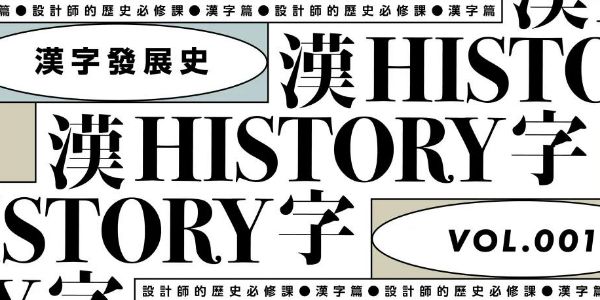
设计师的历史课——汉字篇
良好的学习方法,需要兼顾理论与实践的并行,对于设计学习来说,同样也是如此。而今天要与大家分享的,与这些都无关,却仍然十分重要,它就是历史知识。那么我也不卖关子啦,今天要讲的正是汉字的发展历史。
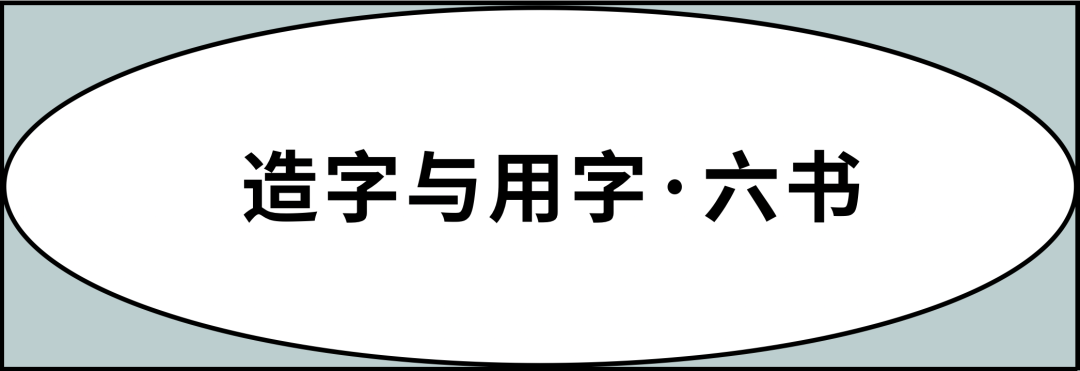
在正式介绍汉字的发展历史之前,我们有必要先来了解一下「六书」。六书,是汉字的六种造字或用字的方法,分为:象形、指事、形声、会意、转注和假借。
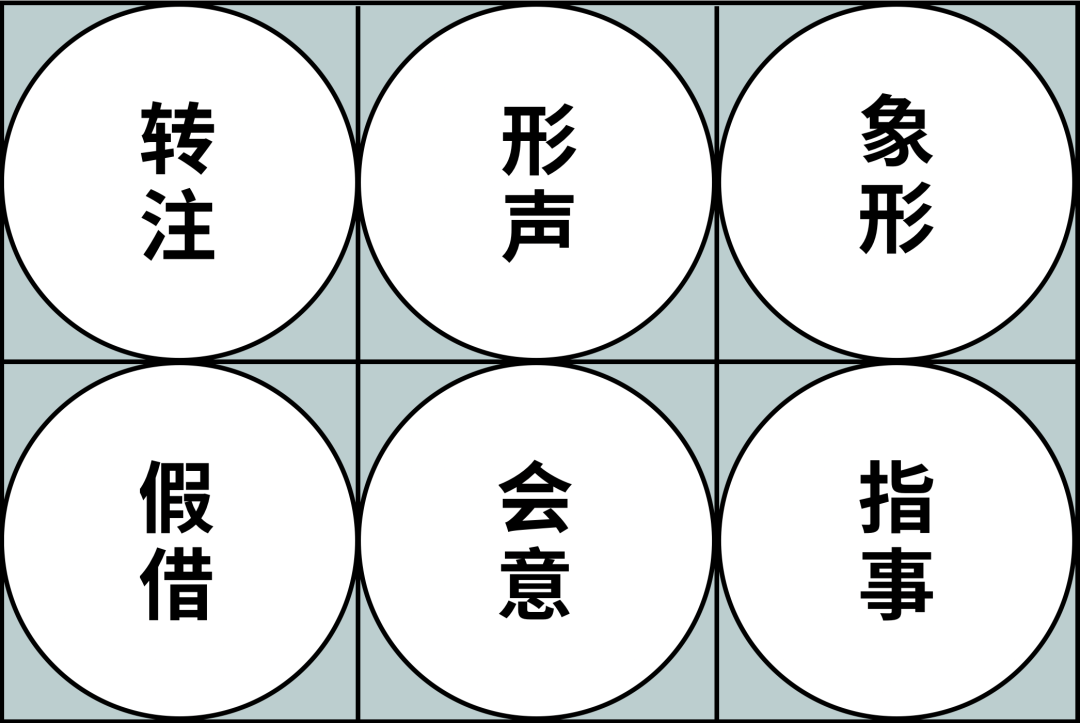
值得注意的是,六书是后人根据汉字的形成所做的归纳整理,它并不是造字公式,却也是我们应尽量追随的造字原则。要知道,现在国内所用的简体字或多或少存在的一些问题,就与脱离了这些标准离不开关系。
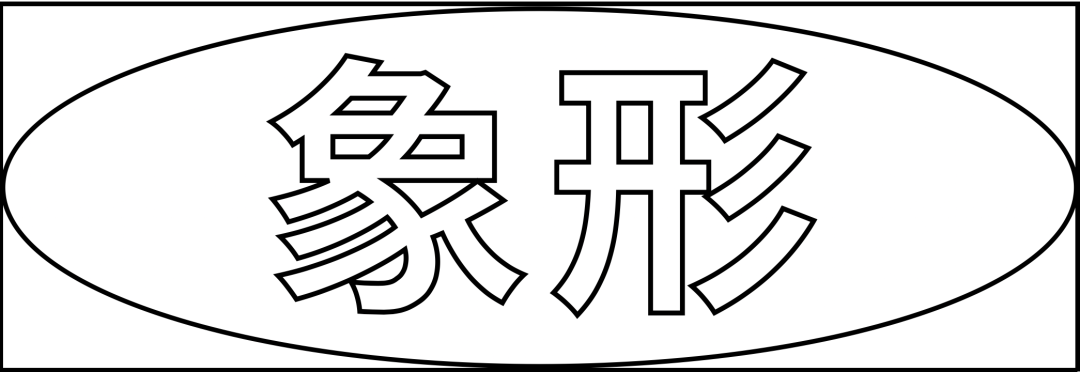
咱们先来说一下象形。象形是指根据具体事物来画出简单概括的图形,它的符号性是很明显的,强调对象的外形特征,因而是一种最简单的造字法。那么相对的,它也是很难去表达抽象的意义或没有具体形象的概念。
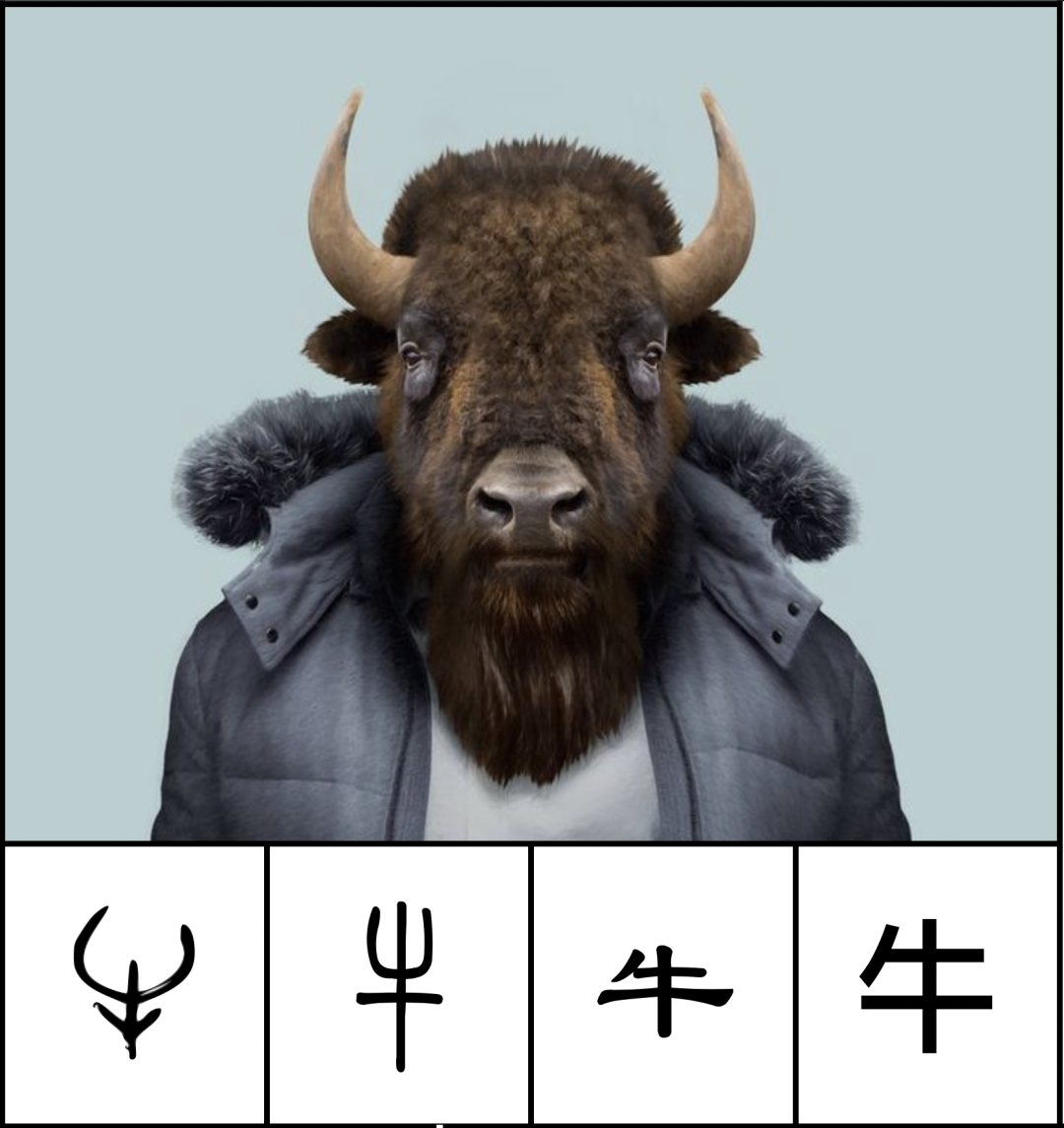
十二生肖中,就有大量的象形字,比如说「牛」字,我们看最左边的甲骨文写法,就很明显能看出是一个牛头的正面概括。
再比如这个「马」字,也是很具有代表性,同样看甲骨文版本,能够清晰地看到马鬣和马腿,并且呈一个两腿跃起的动态,描绘得还是十分生动的。而单看现在所用的简体「马」字,并不会这么明显,但是我们看这个从左往右的演化过程就豁然开朗了,这是一个标准的汉字抽象化的进程。
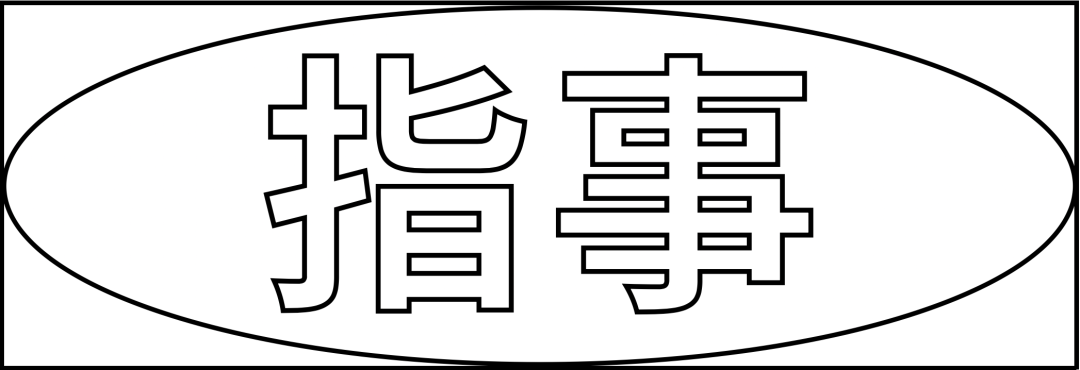
第二个,指事。它通常表示某种局部的或相对的概念。这种造字方法是在象形字的相应部位加上抽象的标志符号;当然,也可以纯粹运用符号来指示所要表达的意义。指事同样也具有较大的局限性,所以在汉字中所占比例较少。
比如说这个「凶」字,他就是一个具象加抽象的组合,半框的结构是描绘了陷阱,然后在陷阱上画出交叉的符号,以此来传递「凶」的概念。
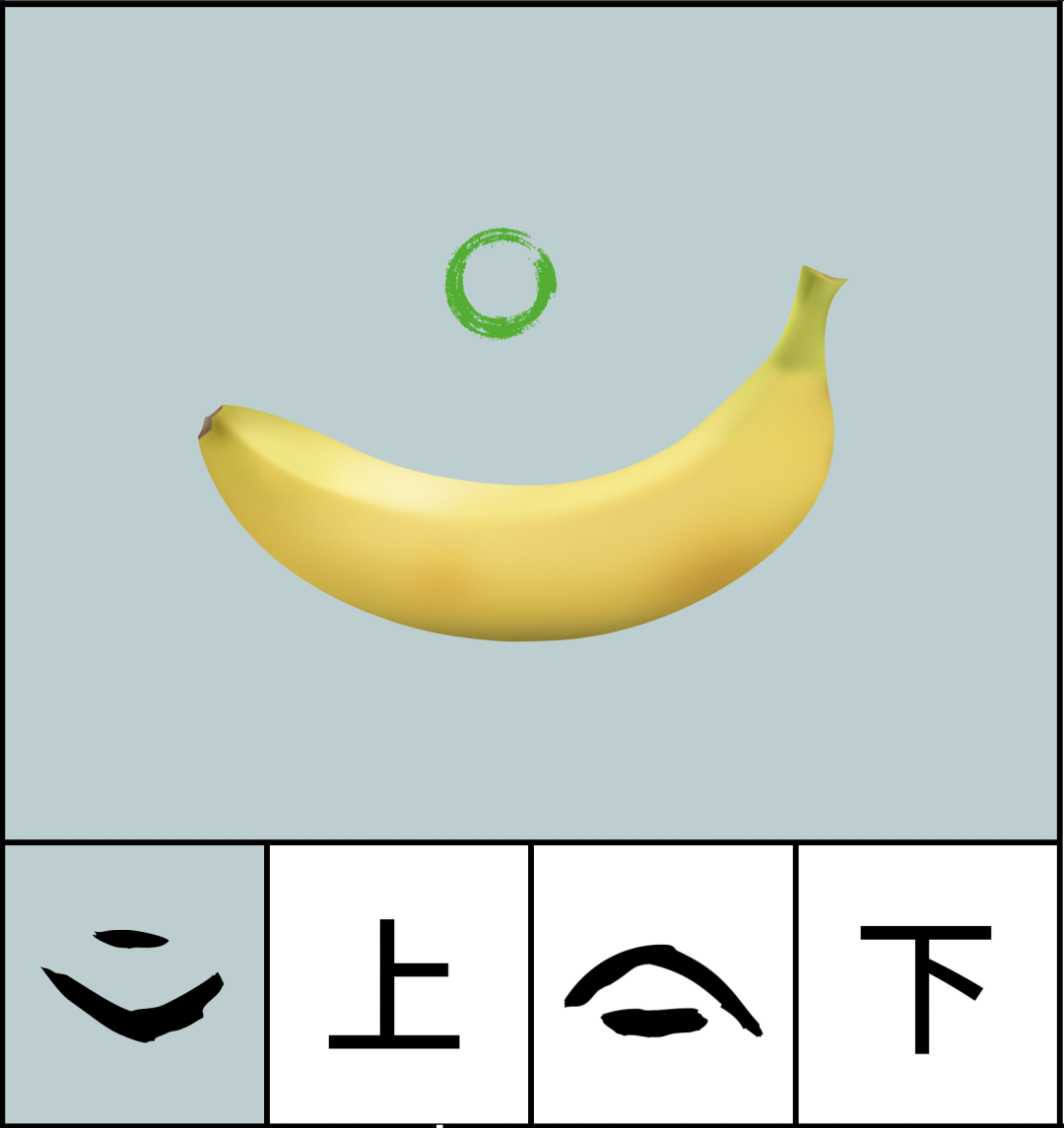
我们可以再来看一下「上」和「下」这两个字,他们的形成方式同样是「指事」,我们可以分解一下甲骨文,把他看做是两部分,长条的笔画是主体,短的则是标记。比如这里拿香蕉做主体参照物,在它的上方做标记,这样就表示是「上」的意思。
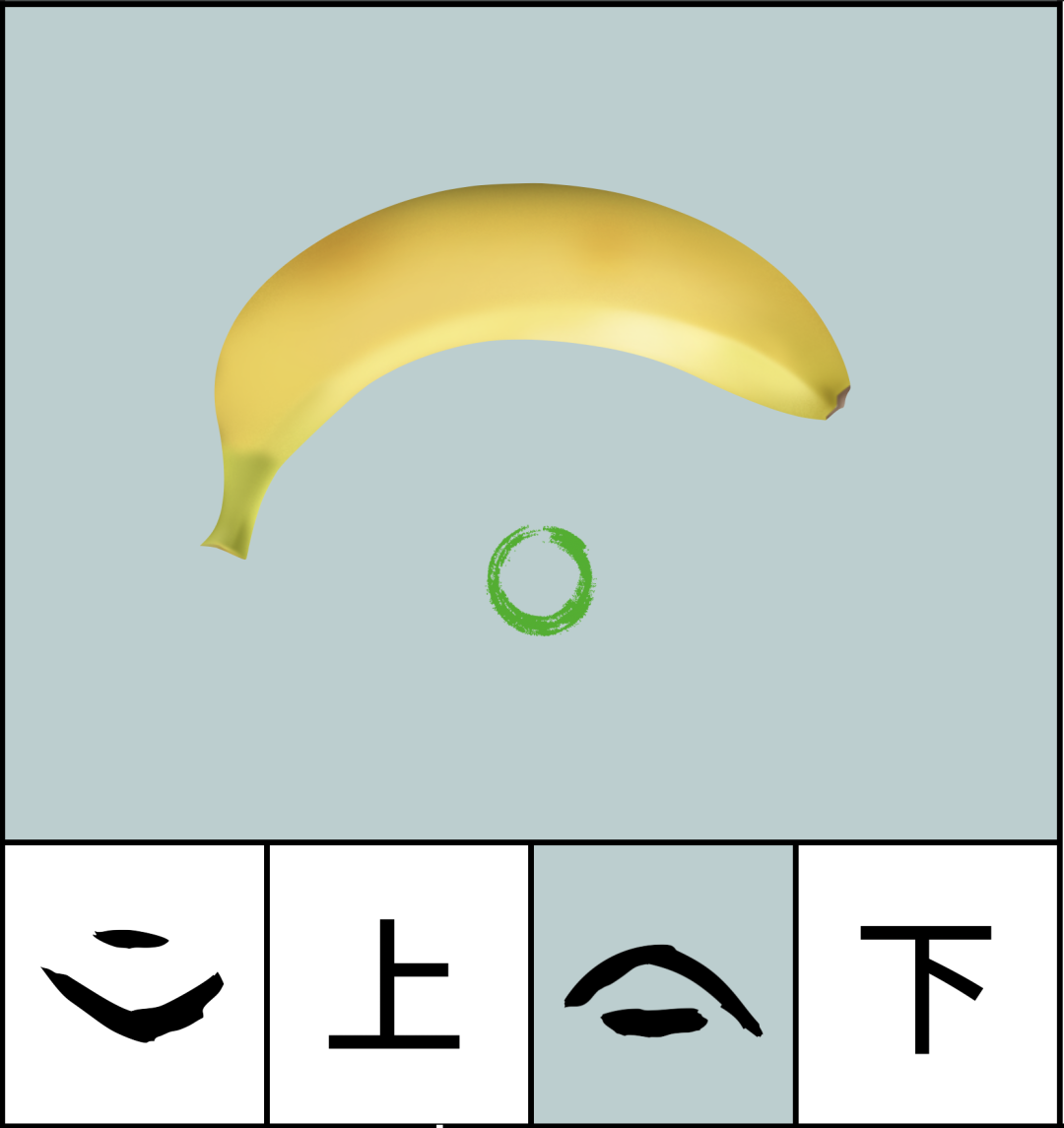
而当标记出现在主体下方的时候,则代表了下。当然,这里拿香蕉做演示,只是为了方便大家理解造字的意思。而实际古人在造字时,这个主体也许并没有实际的意义。
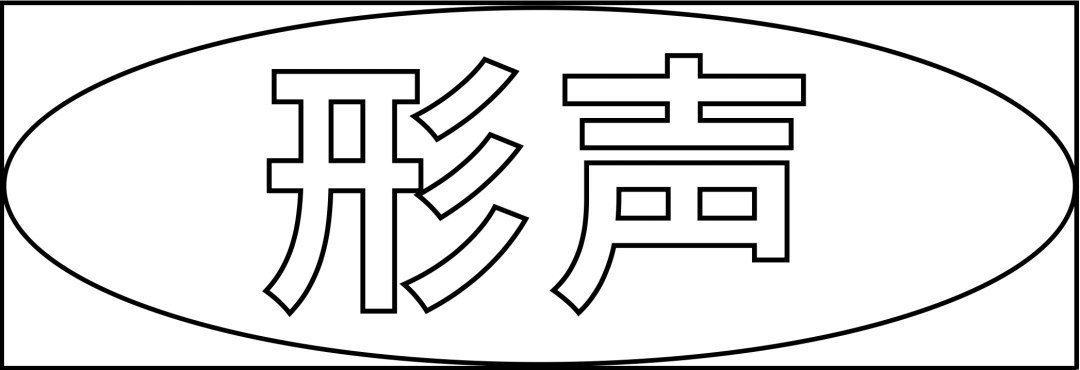
接下来,是「形声」。形声形声,它自然是分为了「形」与「声」。也就是说,它是一种组合型的造字法,字的形旁是表示这个字的意思或类属,而声旁则表示字的相同或相近发音。许多左右和上下结构的字都是形声字,形声字在汉字中数量最多,占80%以上。
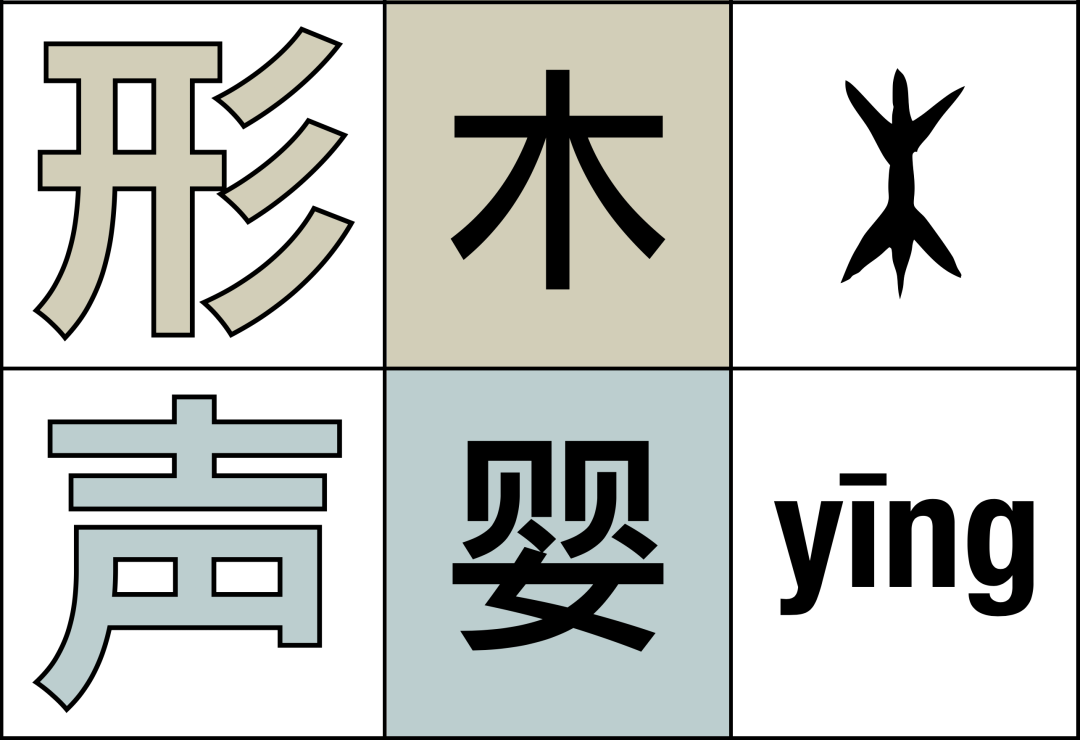
比如说,樱花的「樱」,形旁是左边的「木」,表示它是一种树木;声旁则是右边的「婴」,所以整个字的发音也是「ying」。
再看这个,也许一下子看不出是哪个字的组合,实际上读音已经告诉了我们一切,这是芳草的「芳」字。在隶书以前,并没有大家熟知的草字头,所以代表意义的形部这个字,也念「cǎo」,直到隶变之后,才有了现在的草字头。那么这个字也很明显,「艸」字表示字义,「方」字表示读音。
「形声」之后,我们来说「会意」。它是指由若干符号构成一种联系来表达某种意义,通常是动词、形容词,或者也可以是没有具体形象的名词,这类意义比较抽象,很难用象形的方法来表示。这种造字法还是比较有趣的,仿佛是在用各个部分来叙说一个故事一般。
比如说「盥」字。字义是盥洗、洗手的意思。在甲骨文的写法中,下部是只盆的形状,也就是后来的「皿」,上部是左右两只手,中间还有水。所以,这个字是在向我们阐述了双手在盆里用水这么一件事情,简单说就是洗手。那么这个「盥」字,就是由「皿」、「双手」和「水」三个象形字组合而成的会意字。
再比如说许多人喜闻乐见的「酒」字,它是以酿酒的瓦瓶「酉」和液体 「水」合起来,以此来表达字义。
六书中的最后两种,比起造字法,更可以说是一种用字法。比如书其中的「转注」,它并不是对单个汉字形体结构的说明,而是字与字之间形义关系的一种归类。这种方法,建立了许多的同义字。
比如说「老」与「考」。在古时候,本来在口语里有 「lǎo」 这个字,而没有考,就是说本已制造了「老」字来记录这个读音。
后来口语里起了变化,「老」念成「丂」,写成就是上图下方这个字,而后,又在「丂」的上面注一个同义的「耂」字,它是我们现在用的「老」字的旧写法。
那么组合后,就写成了现在的「考」。「耂(老)」对于「丂(考)」,就是同义相受。「耂(老)」、「丂(考)」的基本意思都是「年纪大」,它们是同义字,当然也是转注字。
最后一个「假借」,是指借用一个字来表达不同的意义,而在读音上也可以有变化。
比如说「长(cháng)」这个字,我们也可以把它念做「zhǎng」。而在不同的读音下,它又可以分别有不同的意思,这一块,并不难理解,我们就点到即止。
介绍完了六书,我们就可以正式开讲汉字的历史了。我们都知道,汉字的发展实际上经历了漫长的演变过程,可以说是历史悠久。同时,汉字也是上古时期各大文字体系中唯一传承至今的。想要了解汉字的历史,我们就需要知道,它分为「古文字阶段」和「隶楷阶段」,下面,就让我们从汉字的起源开始讲起。
说起汉字的起源,大家可能下意识的反应是甲骨文或者金文。但实则不然,无论是它们的哪一种都已经是经过高度发展的。然而,关于汉字起源历来都有不同的说法,以上这六种是比较有影响力的一些说法。
其中,仓颉造字这一说更是充满了神话色彩,最为人所津津乐道。相传仓颉是黄帝时期的史官,汉字的创造者,拥有四只眼睛。而有现代学者认为,成系统的文字工具不可能完全由一个人创造出来,如果历史上真的有仓颉这个人,应该是文字整理者或颁布者。
起源以后,就是大家最常听到的甲骨文了。
甲骨文是我国已发现的最早的文字了,之所以要称作为甲骨文,是因为这种文字总是刻在乌龟甲壳和牛的肩胛骨上。那时候,甲骨是商王与先祖灵魂沟通的媒介,也就是我们现在所说的占卜。而甲骨上的字基本都是关于问卜的内容和得到的答案,有时候还会将结果是否灵验也记录在其中。
有的同学可能会好奇,究竟是如何与先祖沟通的,简单地说,就是占卜师通过过程中甲骨受高温而产生的裂纹来进行翻译。大家可以看这块龟壳上的,大致分为三种图案,中间竖排的就是甲骨文,而在两边对称排列的,由代表序号一二三四的字符,还有就是用来占卜的字符。
而这种一竖一横构成的图案,实际上是占卜师预先刻下,方便龟壳在灼烧后产生裂纹,来读取占卜结果的。仔细观察的话不难发现,这个图案与我们现在所书写的「卜」字十分相像,有理由相信他们肯定是一脉相承的。
接下来,就是金文了。古代称铜为金,所以铸刻在青铜器上的文字叫做金文。
商代的青铜器上就已经刻有金文。至西周时,青铜器上金文已经较为普遍。一般来说,铭文经常只有一个字,可能是姓氏或者是族徽。
但也有比较长的,记述器皿问世的经过、谁下令制作的、纪念某人或某件事。
商代金文多为象形字以及由象形字合成的会意字。这些字像一幅幅图画,生动逼真,比甲骨文还形象。按照汉字的抽象化发展趋势来看,那岂不是金文会比甲骨文的年代感更久远一些?
这里就会牵扯到一个制作方法不同的问题,甲骨文是用刀子刻在坚硬的甲骨上;金文是借助一把勺子在柔软泥土制成的模子上浇铸成形。可以说制作的难度就不相同,而功能上也不同。一些学者认为,当时的人们是在有意识的使用一些更古老的文字,以达到装饰目的。
比如说我们现在制作印章,同样会选择篆书等比较古老的字体。我们通过篆体和黑体的直观比较就能看出,哪一边更加具有玩味。
无论怎样,金文都有着它独特的价值,并且金文还是汉字第一个标准字体——小篆的源头。有同学可能就要问了:听说篆书分为大篆和小篆,为什么这里直接就从金文过渡到了小篆呢?
实际上无论是金文,还是我们没有细讲的一种雕刻在石鼓上的石鼓文,都是篆书,这些古文理论上都可以归类为大篆。说完大篆,我们就可以进一步来介绍小篆了。
春秋战国时期,文字应用越来越广泛,文字趋向于简化,各诸侯国纷争不统一,从而形成了「言语异声,文字异形」的局面 。
比如说「马」这个字,光写法就有七种不同的样式,随着历史的演进,秦皇远交近攻,统一全国后,便结束了这样的局面。
公元前221年,秦始皇命令李斯制定全国统一的标准字体。李斯在大篆的基础上,对文字进行了简化和整理,取消其他六国的文字,创制了统一的汉字书写形式——小篆。小篆相对于之前的各种字体显得更加匀称化、抽象化。
《峄山刻石》
通过这个作品我们可以看到,为了匀称,它的行笔会时而弯曲时而平直。这样变化,让文字与本身象形的形态不再高度一致,象形程度越来越低。
不难看出,这样的篆书笔画不仅横平竖直,曲折也是婉转顺畅。它的字形有长有方,在空间上追求均衡对称,在笔画追求粗细匀称,是十分富有装饰美感的书体。
秦代中期,小篆又逐渐被更加方便和简化的隶书所取代。这是中国文字发展史的一个重要转折点。中国文字结束了古文字时期,进入更为定型的新阶段,也就是之前提到的「隶楷阶段」。
那么说到隶书,就一定离不开这位叫做程邈的男人了。相传隶书正是由他从篆书中改良而来的。原本因得罪了秦始皇而入狱的他,决定在狱中将功赎过。
有感于当时的小篆,虽然作为全国统一文字,在处理公务和书文时,仍然不便于速写,效率低下,所以潜心研究,历经十年最终创出三千隶字。秦始皇看了程邈整理的文字,非常高兴,不仅免了程邈的罪,还将他封为御史。由于程邈的官职属于「隶」,所以人们就把他整理的文字叫隶书。
汉字由甲骨文渐渐演变为隶书,之所以笔画形态会产生这样的变化,实际上最主要的还是受了毛笔书写的影响。
那时候,人们在日常生活中书写的文字就具有了毛笔的特点,隶书不再是小篆那样粗细均匀的笔画与方正圆融的字形,跟没有甲骨文那样的刻划感。
而隶书的书写效果由早期古隶的多边字形,到东汉时期逐渐成为规范,变得略微宽扁,横划长而竖划短,呈长方形的样子,空间上更加讲究对比。
其中笔画造型最独特的,是很多字都会有一笔「波划」,也就是向右伸展的长横划。比如这里「十」字的横画就是如此,它讲究蚕头燕尾,一波三折。
隶书之后再到楷书。楷书大家相对会比较熟一点,因为时至今日,它仍然是最常用的汉字书体。
楷书是从隶书演变而成的字体,又称为「真书」或者「正楷」,它起始于东汉,在三国时期渐成规模,最终盛行于唐代。
三国时期的著名书法家钟繇被认为是楷书的始祖,他与大家熟知的书法家王羲之并称为「钟王」,据说名义上钟繇还是王羲之的师公。
他的楷体自成一家,笔力均衡,刚柔并济,既传承了隶书中的古雅,又有他自己独特的风格。
唐代的书法名家辈出,欧阳询、颜真卿、褚遂良、柳公权等我们都是耳熟能详的,他们都被视为楷书典范。
《多宝塔碑》
就拿颜真卿来说,现在我们都能看到一些楷书字体标有它的署名,包括一些宋代的课本,这类字体我们可以统称为颜体。颜真卿是中国唐朝的一位政治家,也以书法家闻名于世。他在安史之乱中建立大功,后被派遣去招降叛乱领袖李希烈而被捕,因为拒绝投降而被杀害。他的字也犹如他的性格般刚直有力,图中的《多宝塔碑》是他的代表作品之一。
不过黑体起初只有一种笔画粗细度,而由于汉字笔划多,这会导致小字黑体清晰度较差,并不适合用来编排内文。所以一开始黑体主要用于报刊中的文章标题。
但随着制字技术的改进,和字体家族的出现,不同自重和宽窄体让用字更加灵活,适用于正文的黑体字形自然也变多了。
与宋体相同,黑体也有其他称呼,它还被称作哥特体,像日本就通常以此为称呼。
不过需要注意的是,另外一种由12世纪发展出来的手写字体也叫哥特体,不过他们并没有什么关联。12世纪的这种哥特体笔画粗细对比明显,末端含有衬线,明显与黑体的等粗无衬线感觉不同。
到这里,关于汉字的演变历史已经全部讲完了,今天我们虽然没有讲字体设计,但是了解字体历史却会让我们受益良多。实际上,许多字体作品正是借鉴学习了优秀的古帖、古碑,才能显得既正统又创新。所以我们在创作的时候,同样可以向书法名家学习,站在巨人的肩膀上,可以看到别样的风景。而了解同一个字的不同写法和发展,也会让你更好的应对不同气质的项目。